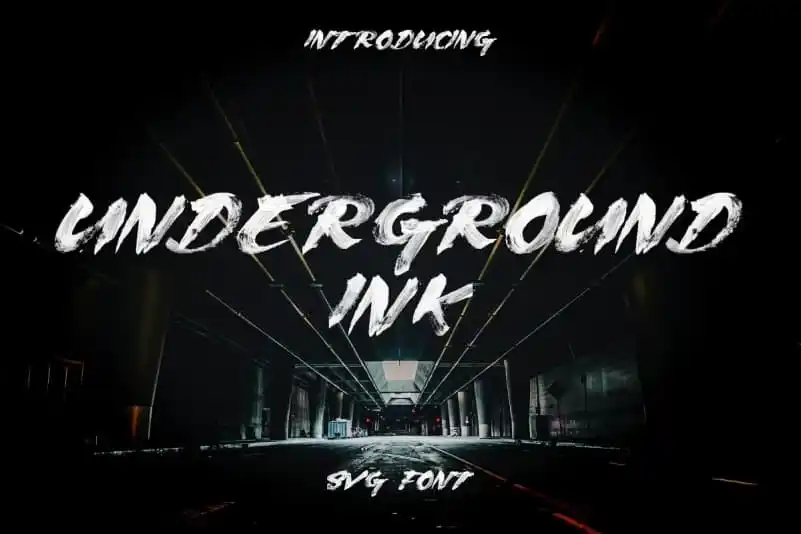
A Underground Brush Font é uma nova adição à coleção dos tipos de letra Script Fonts, criada pela Surplus Type Co. Esta fonte, embora apresente traços retos e totalmente em letras maiúsculas, destaca-se com sua textura do desenho a água incorporada. Ela oferece um toque único e inusitado, caracterizado por seu itálico peculiar e caracteres sujos e borrados, que parecem tão reais quanto possíveis. Ideal para projetos exigindo elementos de tipo “grungy” ou “grittys”, a Underground Brush Font é uma escolha perfeita. Sua textura única e sua consistência em diferentes idiomas tornam-a um recurso valioso para designers gráficos, ilustradores e criativos de todo o Brasil e mais longe. Ela promete transformar qualquer design em algo quirkier e realista, dando aos seus projetos uma identidade visual única e vibrante. Se você busca uma fonte que ofereça um toque único e moderno ao seu trabalho, a Underground Brush Font pode ser sua melhor opção.